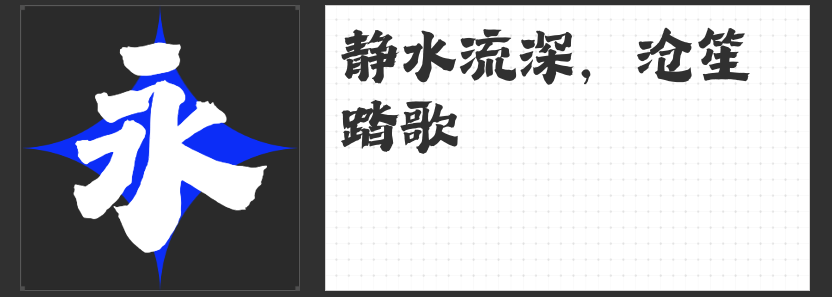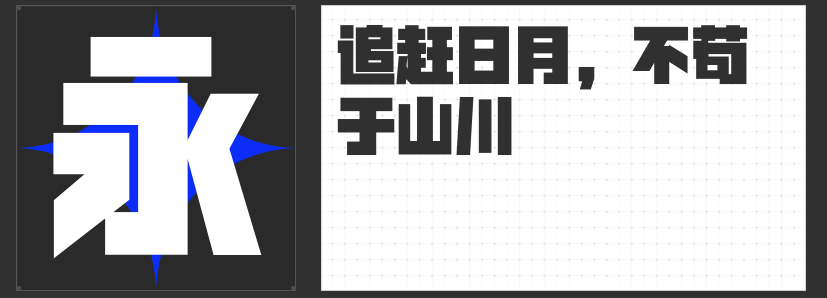
国庆设计必备:四款彰显大国风范的创意字体推荐
国庆节是中国最重要的节日之一,它不仅是庆祝国家成立的日子,也是展示国家文化和精神风貌的重要时刻。在这个特殊的日子里,选择一款能够体现大国风范、彰显民族自豪感的字体,对于各类国庆相关的平面设计、宣传材料和文化创意产品来说至关重要。以下是四款视觉上气势磅礴、能够完美契合国庆主题的创意字体推荐。
1. 造字侠热辣隶简
“造字侠热辣隶简”是一款融合了传统隶书特点与现代设计元素的创意隶书。其整体结构稳定、中宫扁宽,具有极强的视觉冲击力,给人以庄重威严之感。笔画线条简洁明快,撇捺起收笔细粗自然过渡,横笔开张对称,竖钩及弯钩的书写力量以直线高度概括。多样性的笔画既保留了历史感,又富有现代气息。这款字体适用于国潮设计、教育、文化产品包装、海报以及品牌塑造等应用场景,能够为设计增添浓厚的文化底蕴和时代感。
2. 造字侠朝凤宋简
“造字侠朝凤宋简”是一款宽扁工整、软硬兼备、布白均匀的宋体。横笔画起笔左下角带有圆角收笔处,折笔处带有方形特点,撇、捺、提笔画曲线流畅收笔处均带有切笔凸起,点画为切笔半圆形,钩画外圆内方。整体更具几何化,兼备力量感与柔美感,韵美结合,极具表现力。这款字体适用于政府公告、国庆庆典海报、历史文化展览等正式场合,能够传递出一种庄重而优雅的氛围,增强设计的权威性和可信度。
3. 万人字造踏歌行体
“万人字造踏歌行体”结体方整严谨,笔画布局匀称又不失动感。用笔方整又带有圆润且略具斑驳感,笔力劲健,具有蓄势待发之势。整体单字笔画带有古法用笔的感觉,增强了整体风格特征。这款字体适用于国庆主题的文创产品、纪念品设计、传统文化活动宣传等,能够为设计注入一种古典而典雅的韵味,提升作品的文化内涵和艺术价值。
4. 励字开拓者简 特级黑
“励字开拓者简 特级黑”字型方正,中宫较大,重心适中。全部采用直线笔画,笔画横平竖直,棱角分明,笔画特点简约,起笔和收笔以平切为主,内部几何处理空间均匀,整体平衡。部分钩笔画进行去钩处理,撇、捺、点运用竖直的处理方法,带有强烈的镜像视觉效果。励字开拓者系列化共5款家族字体,实现由正文到标题的平滑过渡,适用各场景的应用。此款字体还包含常用的“又、双、叒、叕、囍、雷、靁、䨻、火、炎、焱、燚、水、沝、淼、㵘、牪、龖”等网红流行用字,适用于国庆宣传标语、大型活动海报、政府公告等,能够传递出一种坚定而自信的力量感,增强设计的现代感和视觉冲击力。
总之,这四款字体各具特色,不仅能够满足不同设计需求,还能为国庆相关的各类设计作品增添独特的魅力。无论您是在寻找能够体现传统文化的字体,还是希望为设计注入现代感和力量感,“造字侠热辣隶简”、“造字侠朝凤宋简”、“万人字造踏歌行体”和“励字开拓者简 特级黑”都是不错的选择。希望这些推荐能够为您的国庆设计提供新的灵感与创意。